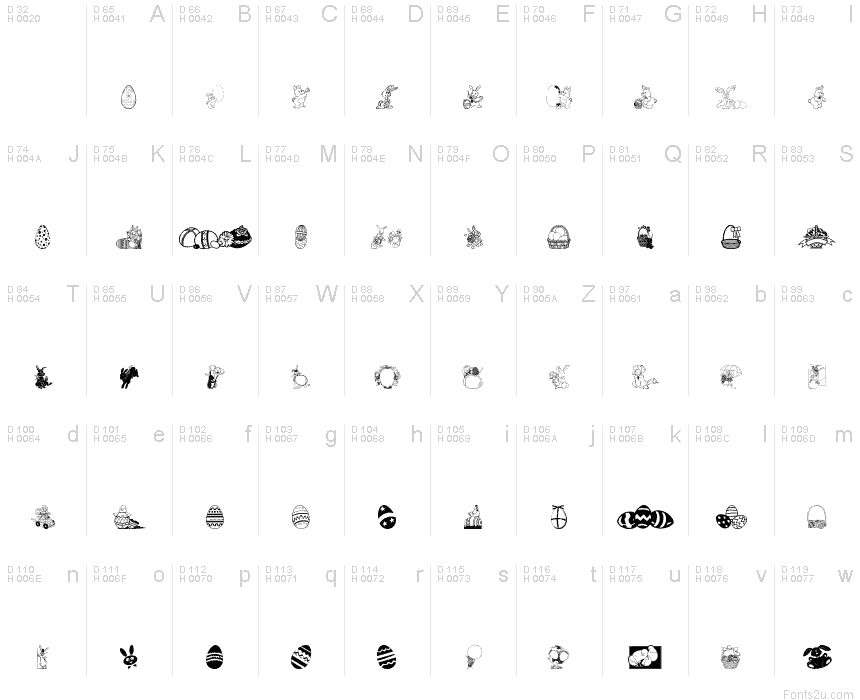
Krój pisma Easter Art od GemFonts98 & Silverfox zamienia Twoją klawiaturę w zestaw darmowych wielkanocnych ilustracji, wyróżniających się lekką kreską i zabawnym, bajkowym stylem. Symbole wyglądają zwiewnie i ręcznie rysowane, a nie mechanicznie, dzięki czemu wprowadzają delikatny, sezonowy nastrój na zaproszeniach, materiałach szkolnych, tabliczkach na poszukiwanie jajek, stronach albumów, bilecikach do prezentów i wiosennych ulotkach.
Ten darmowy font sprawdza się najlepiej, gdy potrzebujesz dekoracji bez ciężkiego, blokowego wyglądu. Easter Art dodaje uroku dziecięcym pracom plastycznym, etykietom piekarniczym, biuletynom, postom w mediach społecznościowych i kartkom do druku, zwłaszcza w połączeniu z prostym krojem bezszeryfowym lub szeryfowym w tekście głównym.
Easter art
GemFonts98 & Silverfox